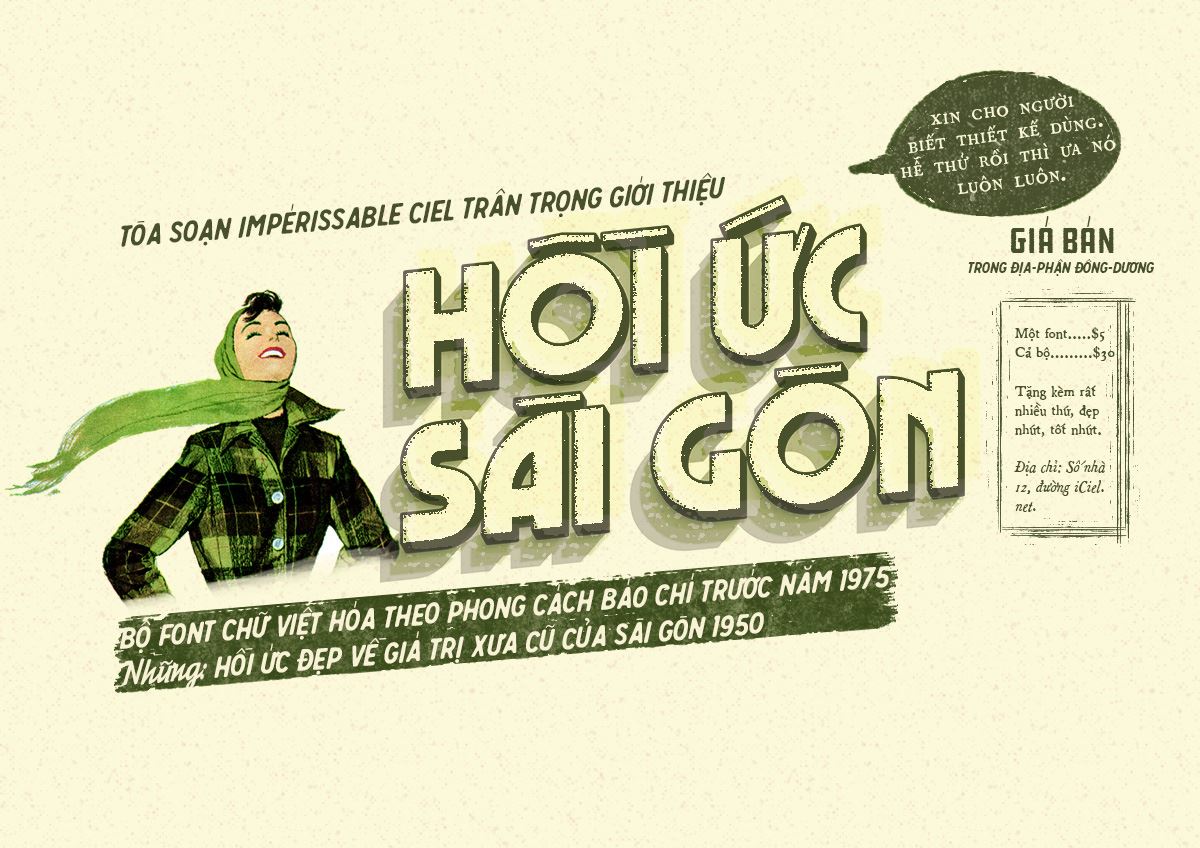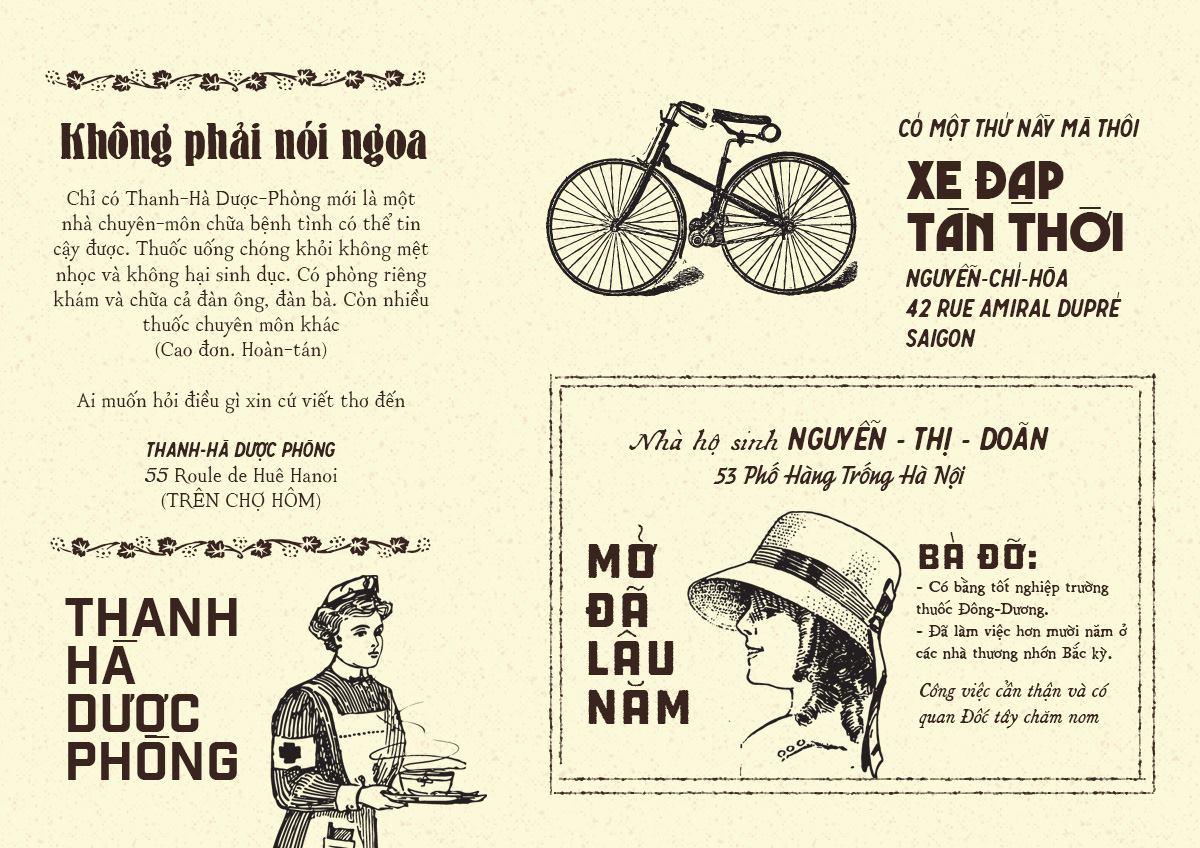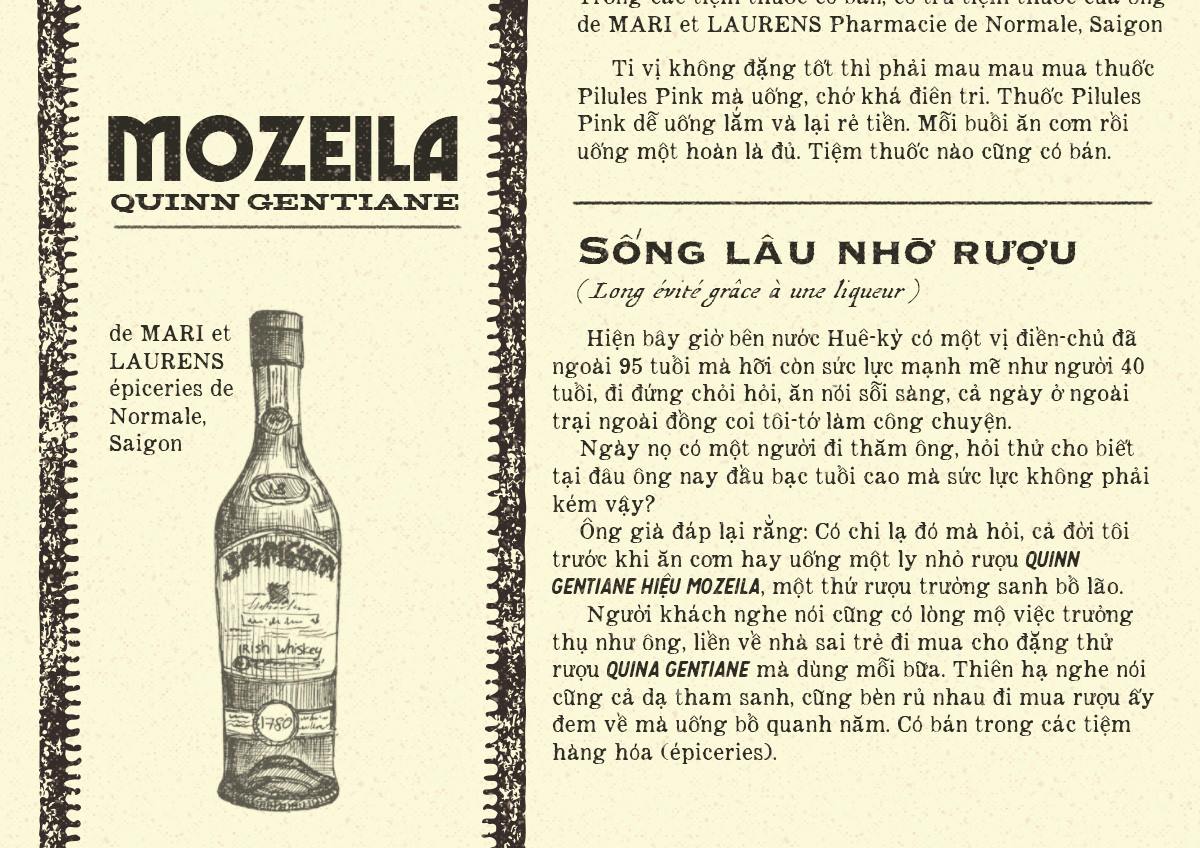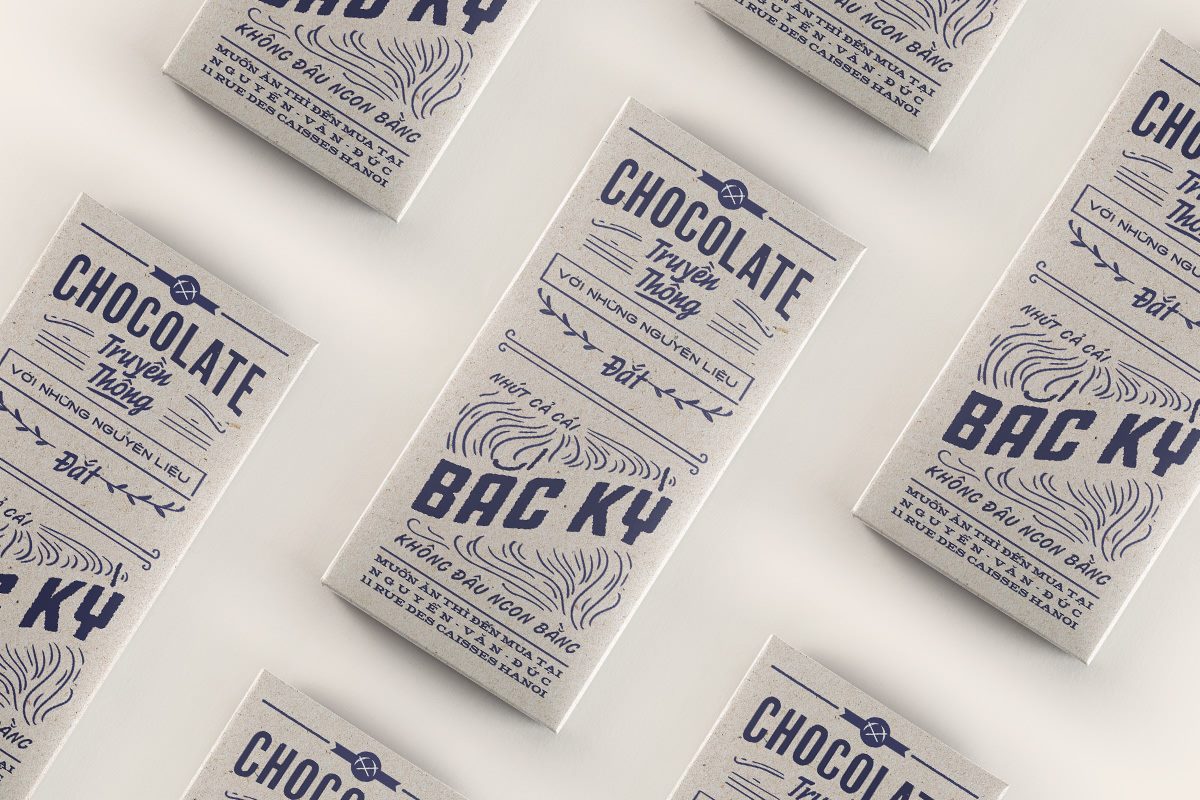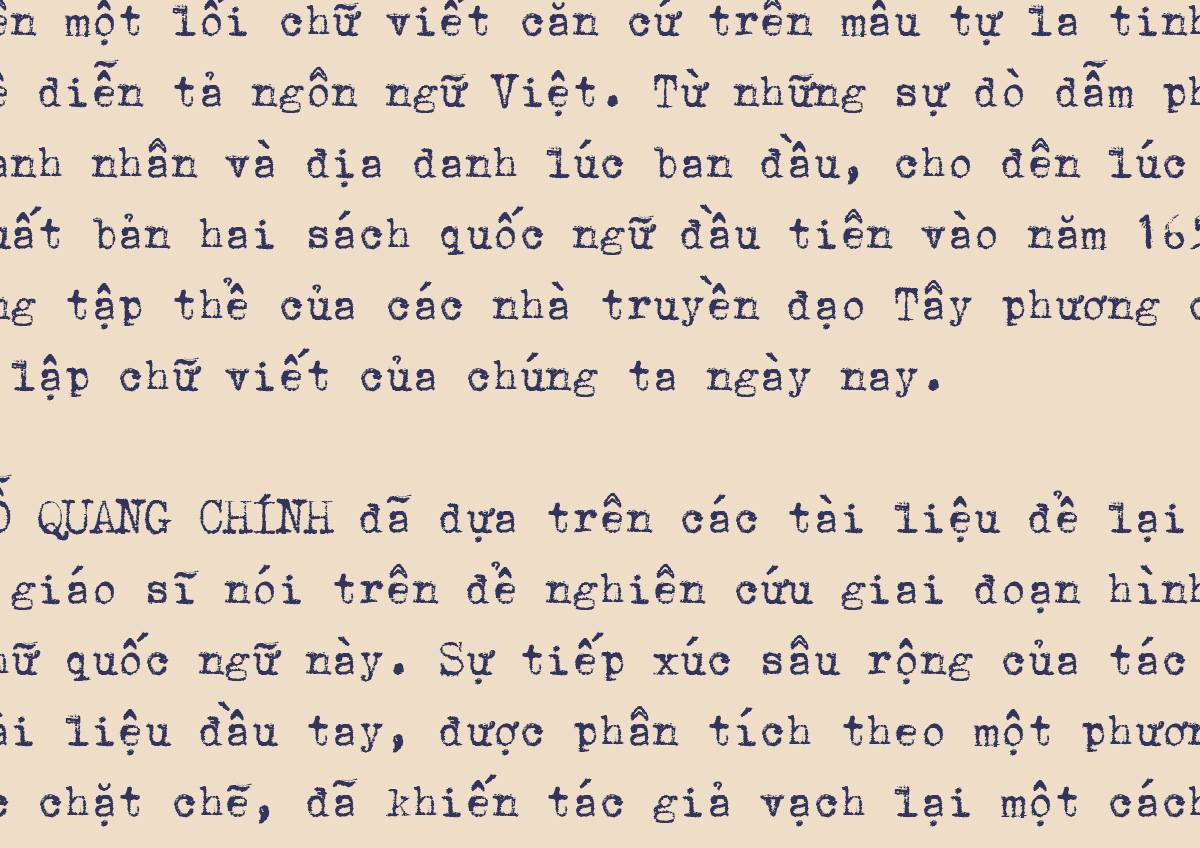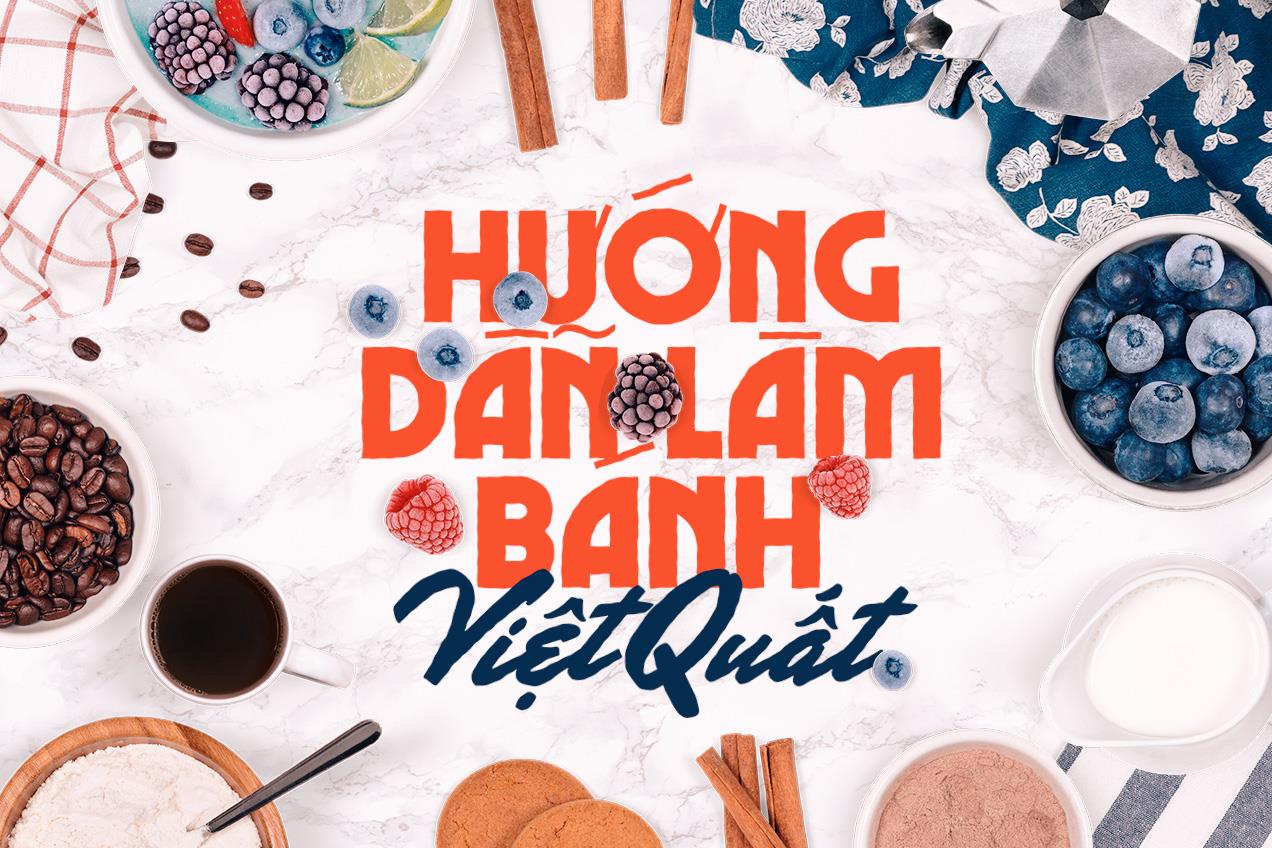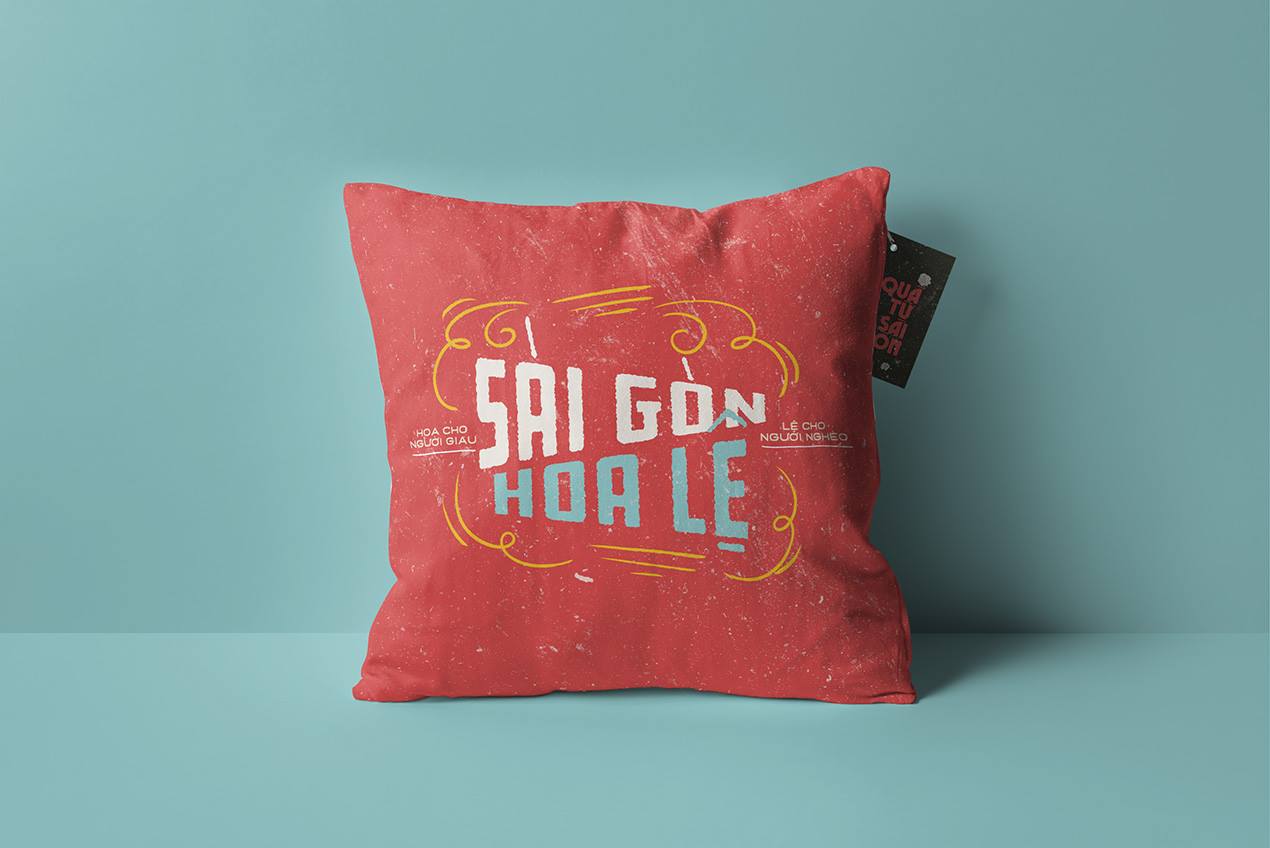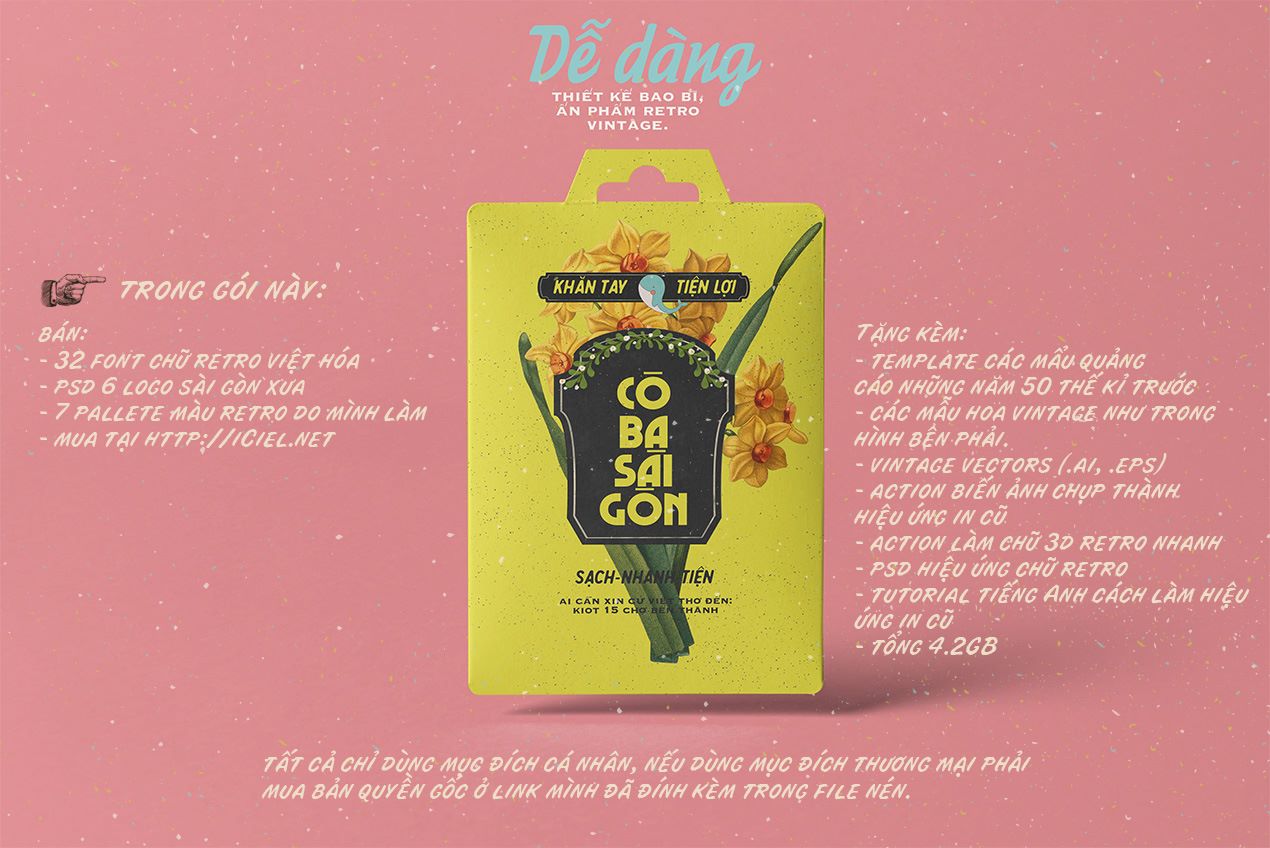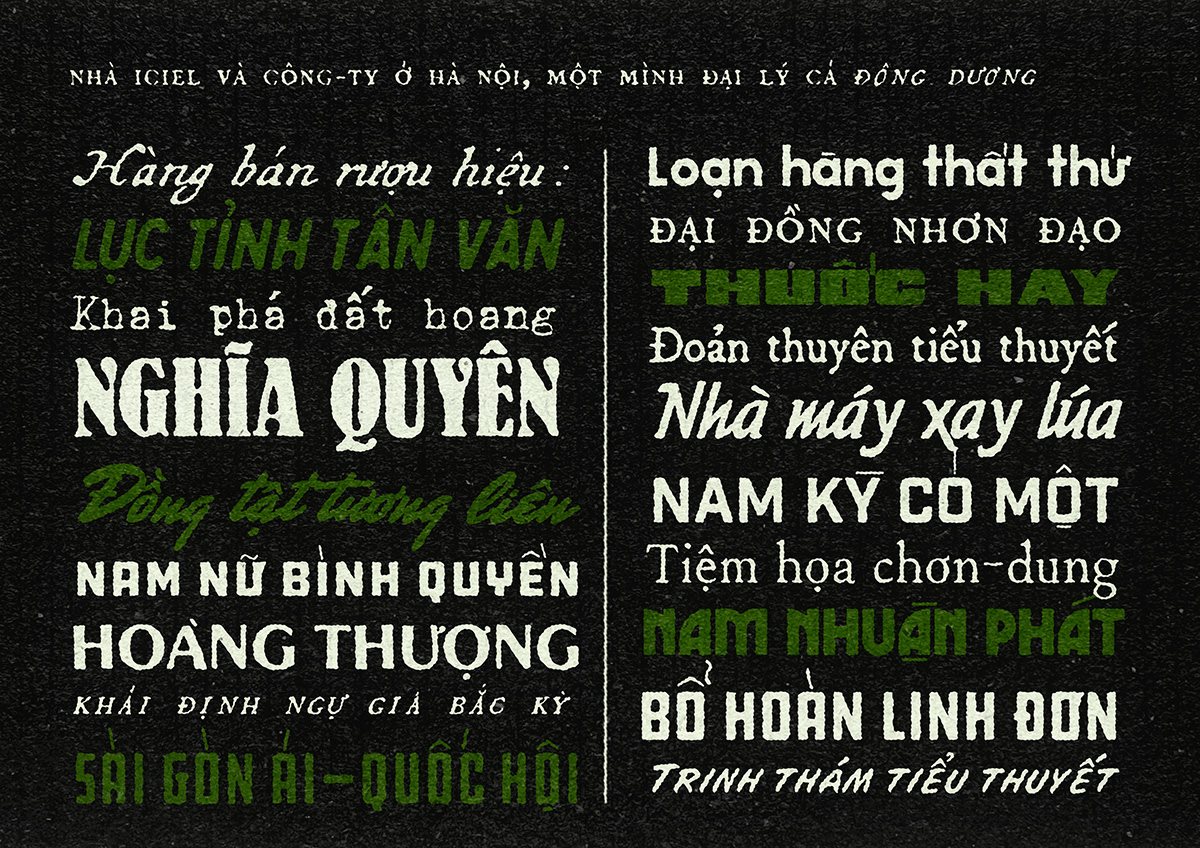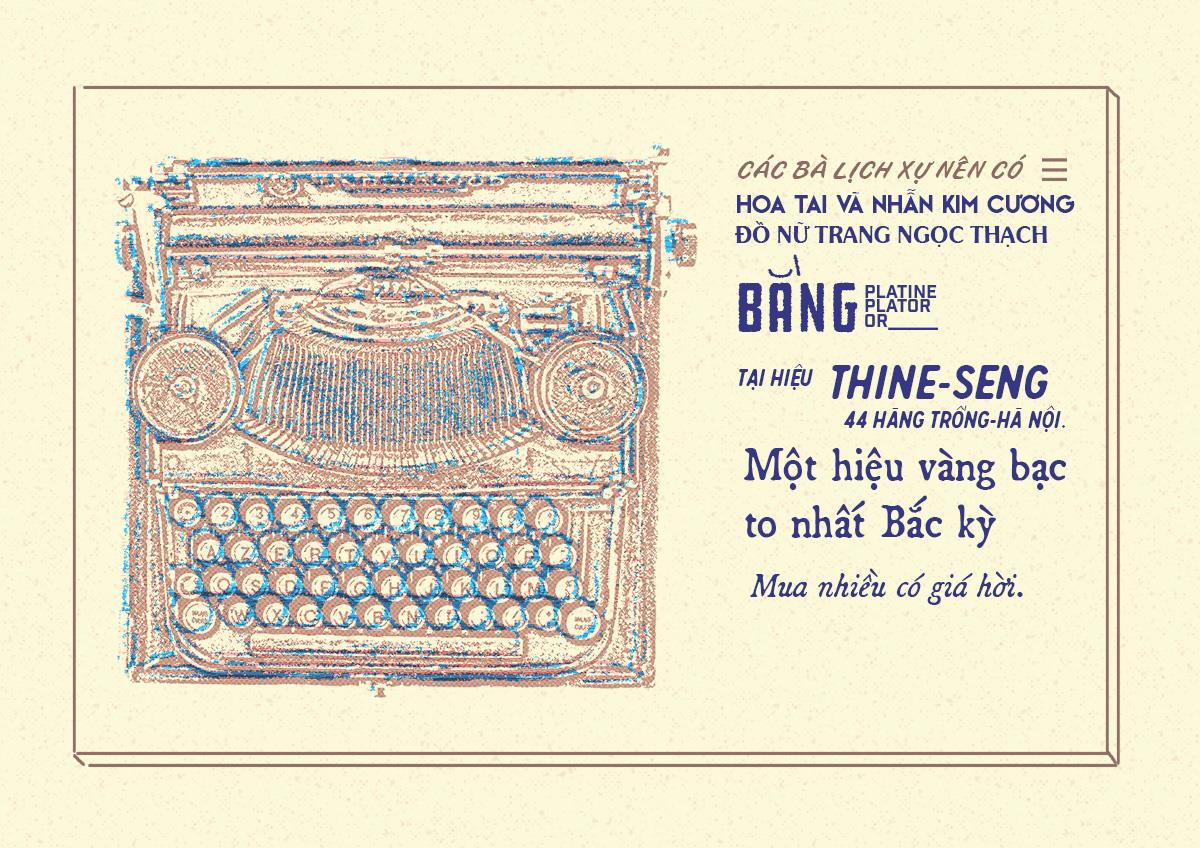
Bộ font lấy cảm hứng từ những hình ảnh về Sài Gòn trước năm 1975, và được tác giả trau chuốt từng ly về các dấu. Không như hai bộ Giá trị xưa cũ và Hòn Ngọc Viễn Đông tập trung vào những chữ viết trên bảng hiệu, thì bộ font Việt Hóa Hồi ức Sài Gòn tập trung chính xác những cuốn sách, tạp chí, báo giấy, tờ rơi quảng cáo, với gần một nửa các font chữ là dạng font cho văn bản dài.